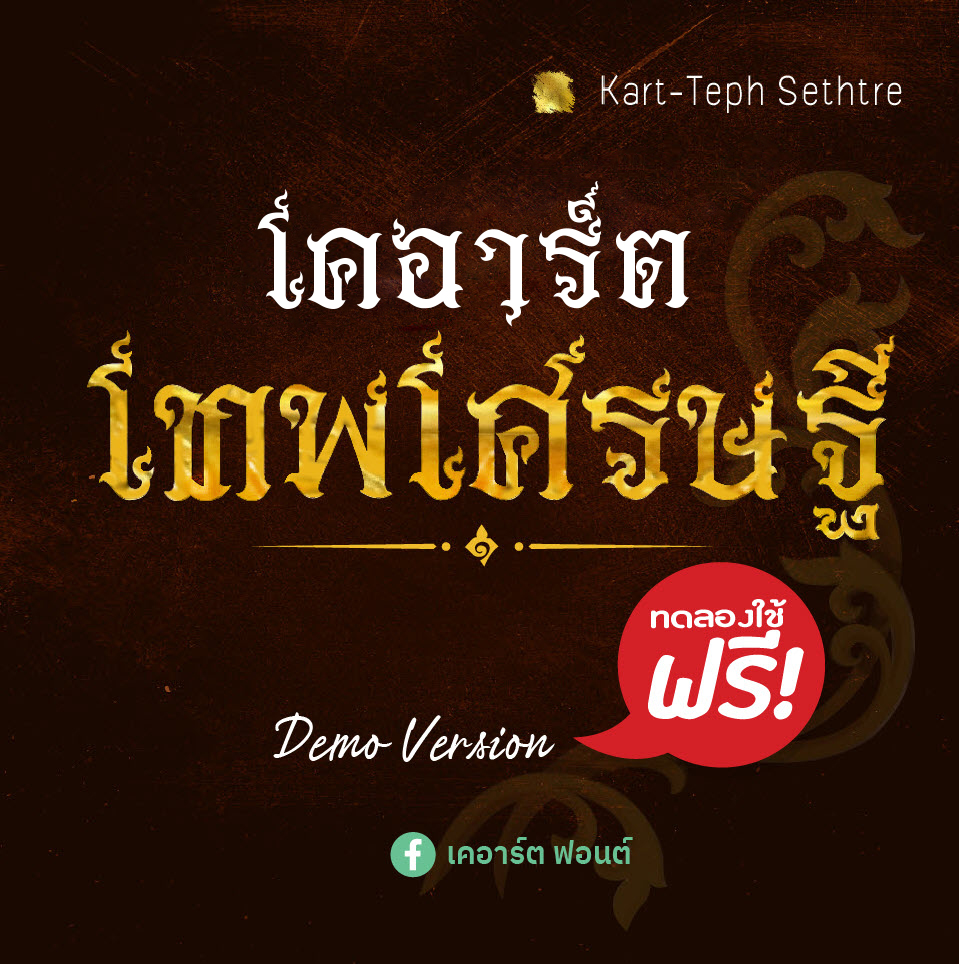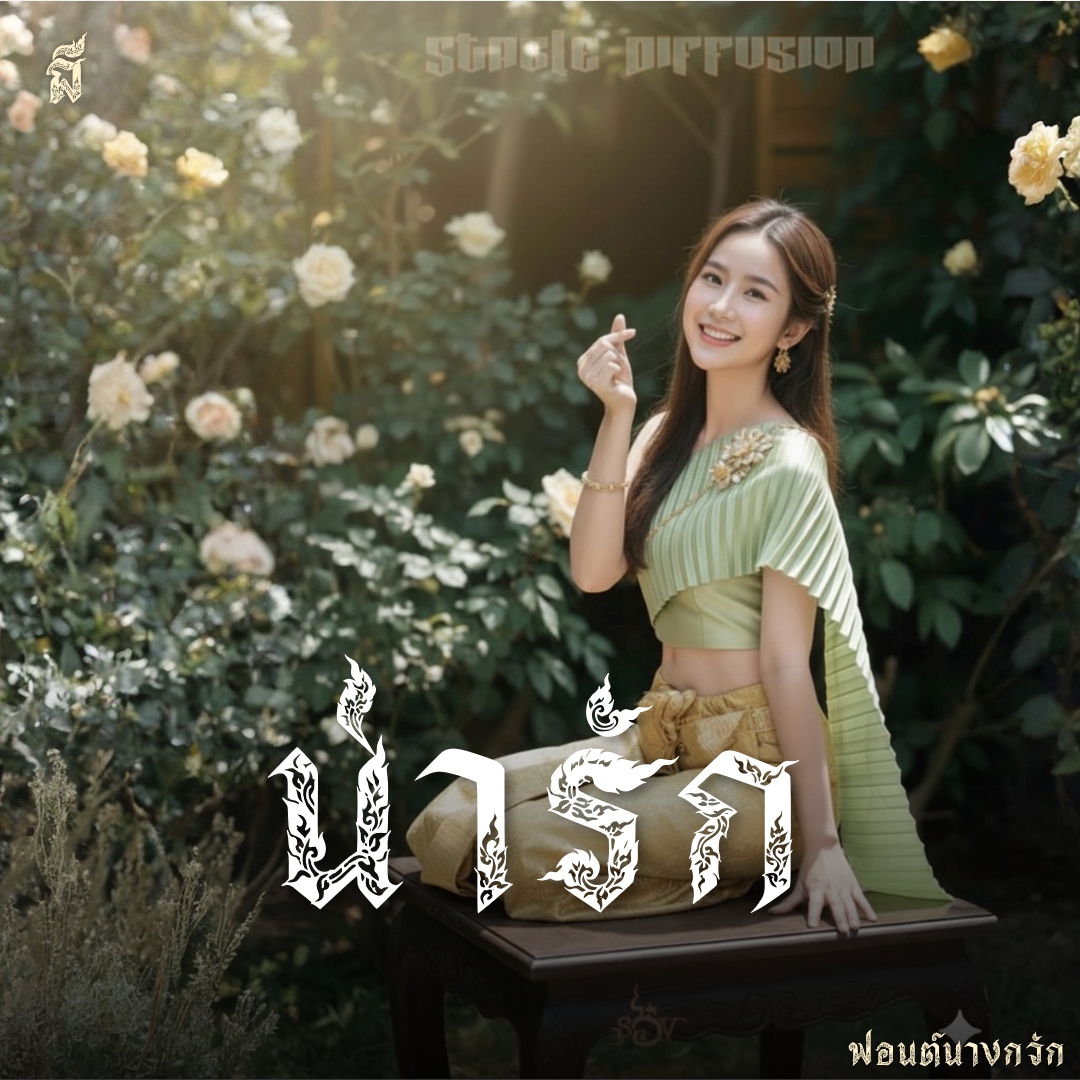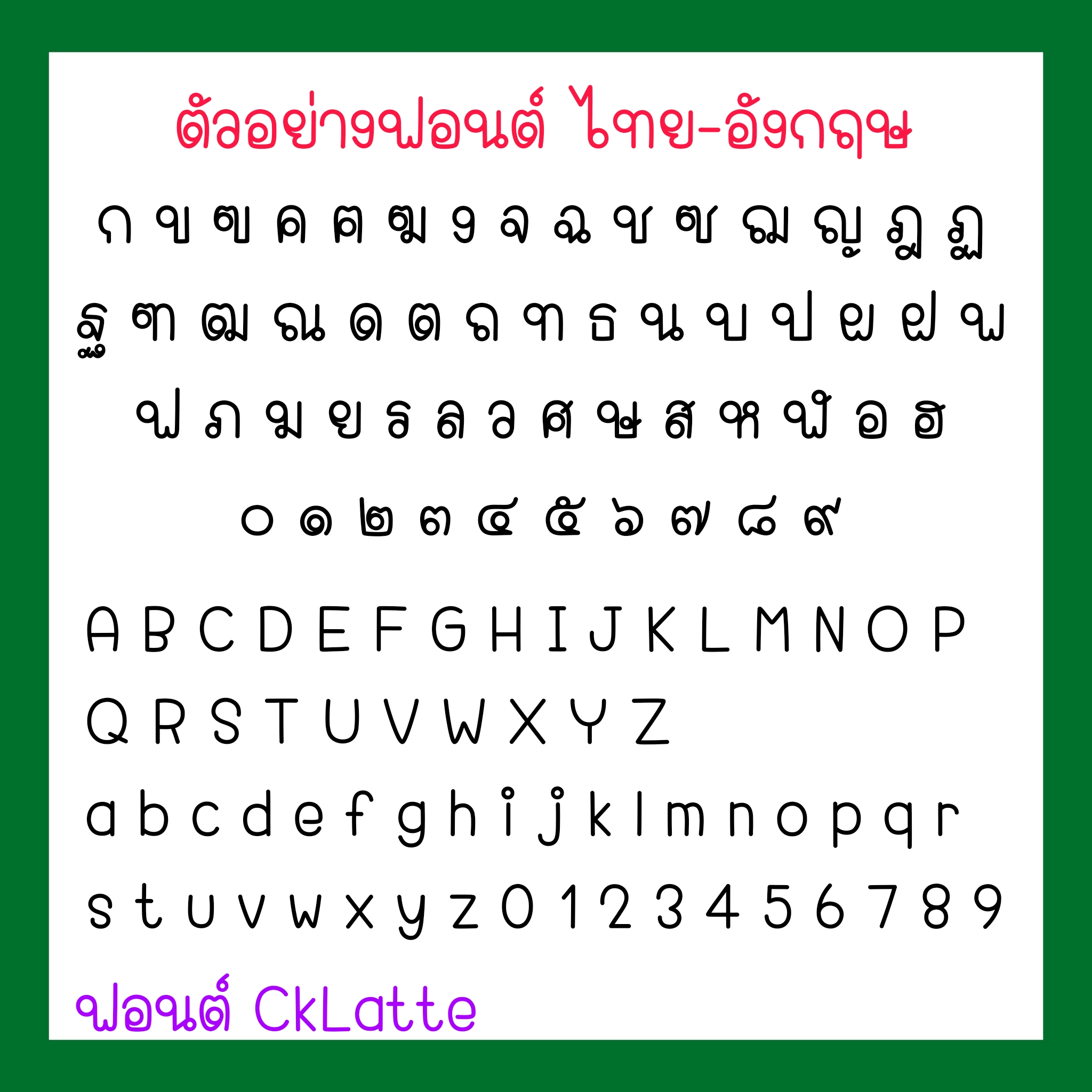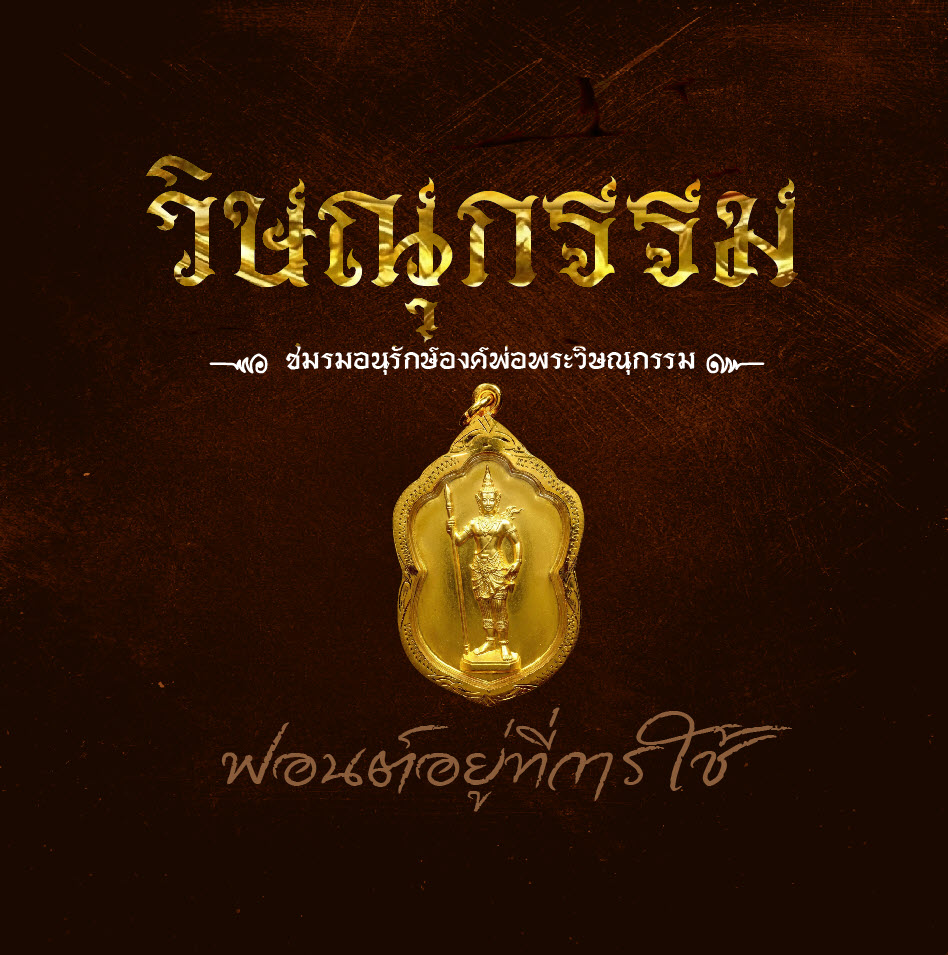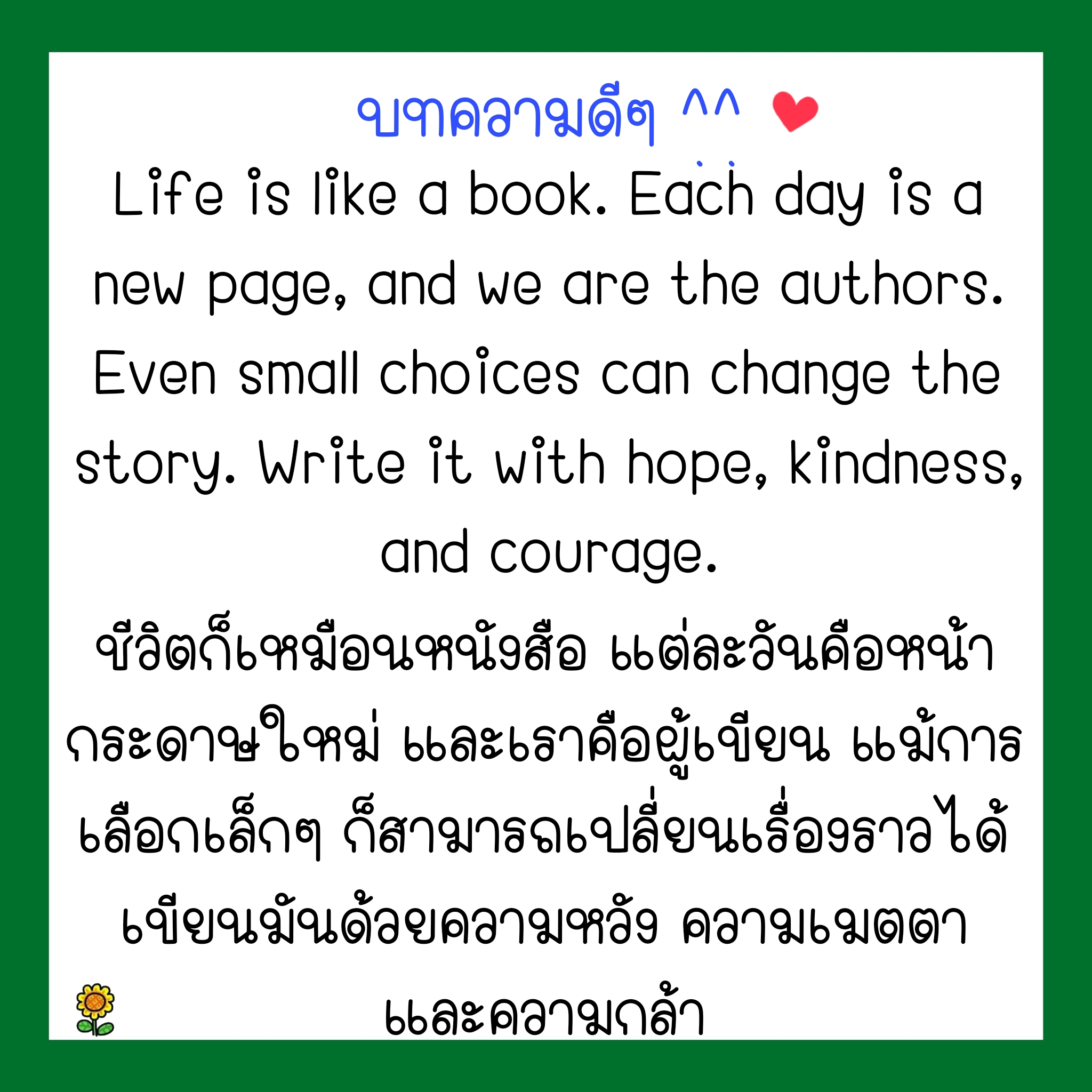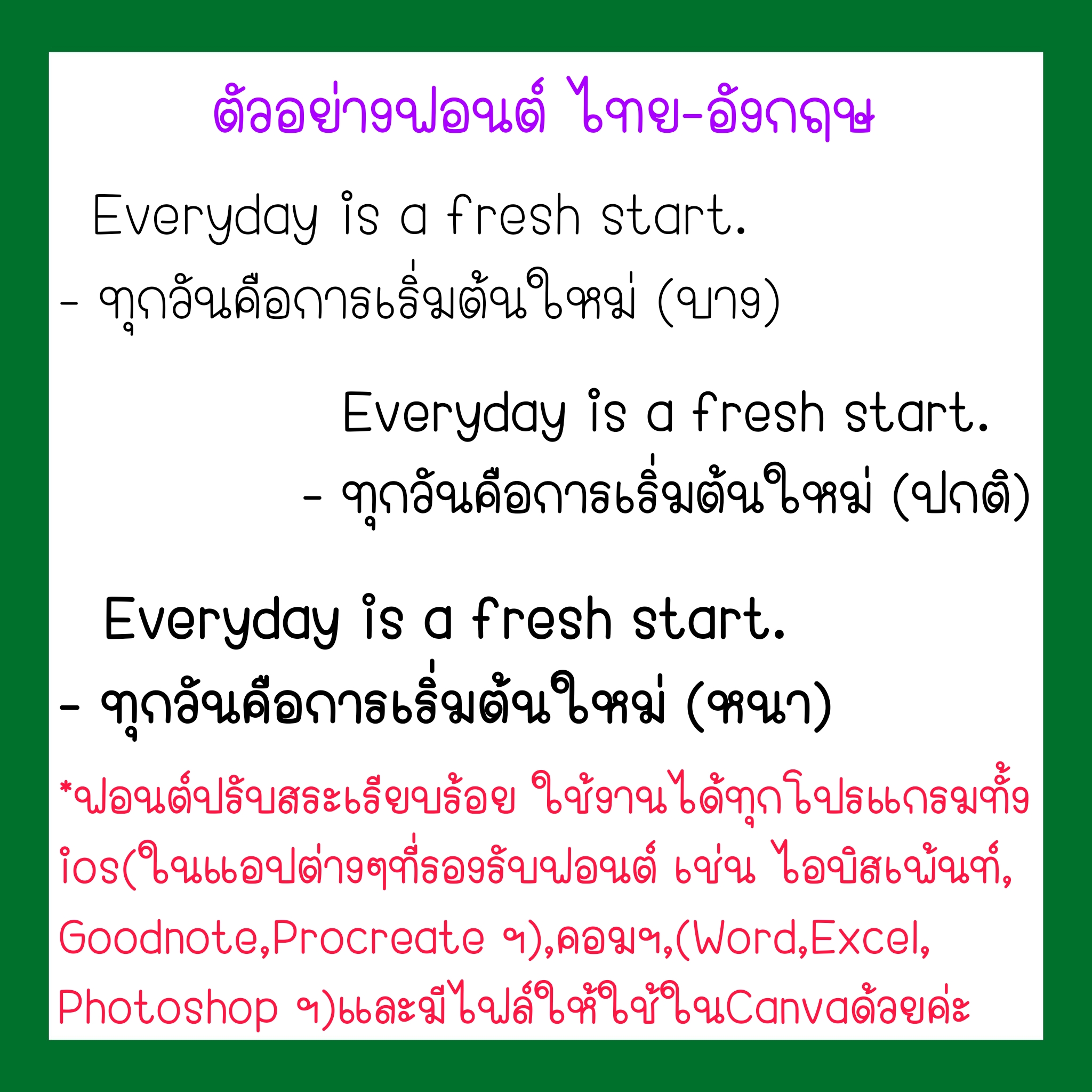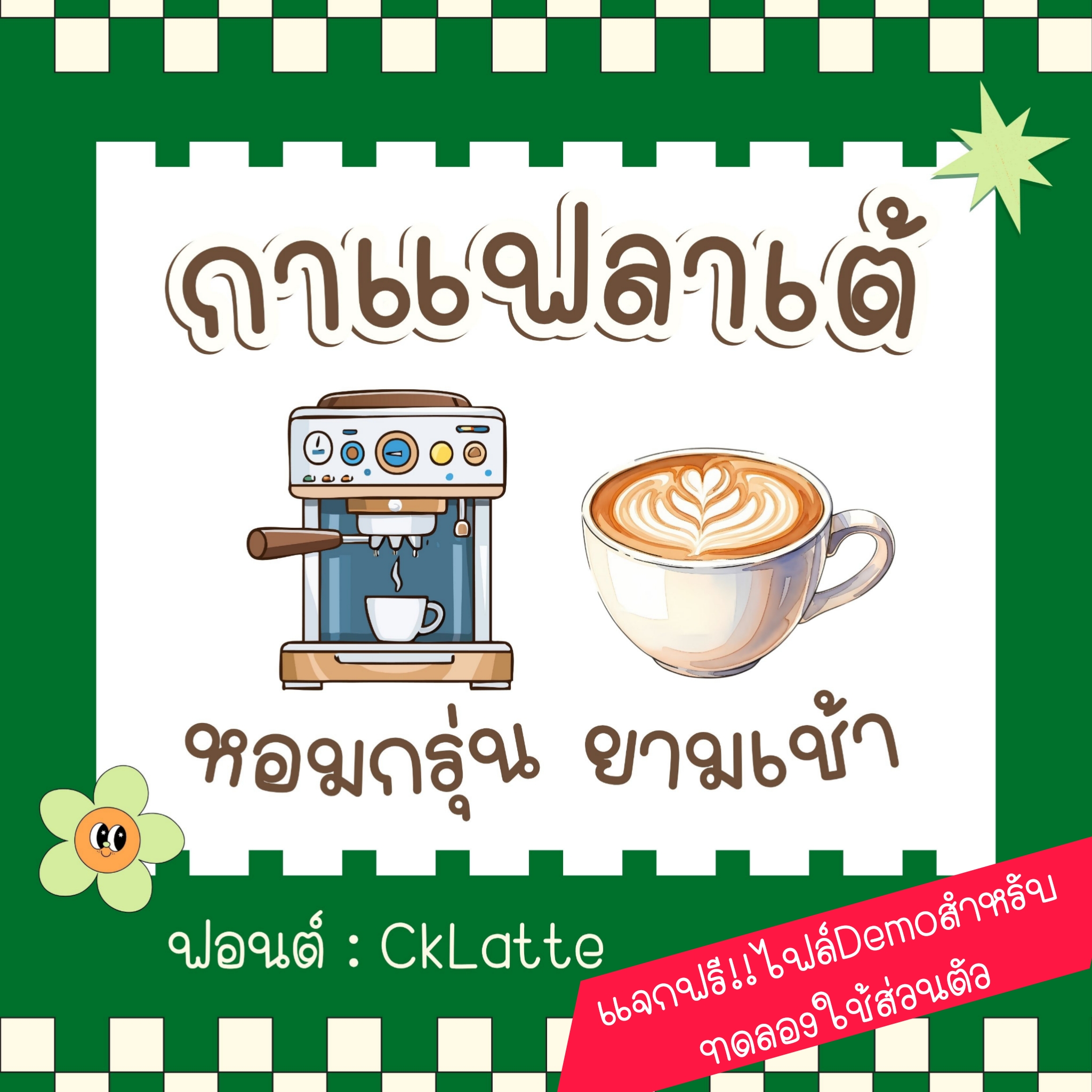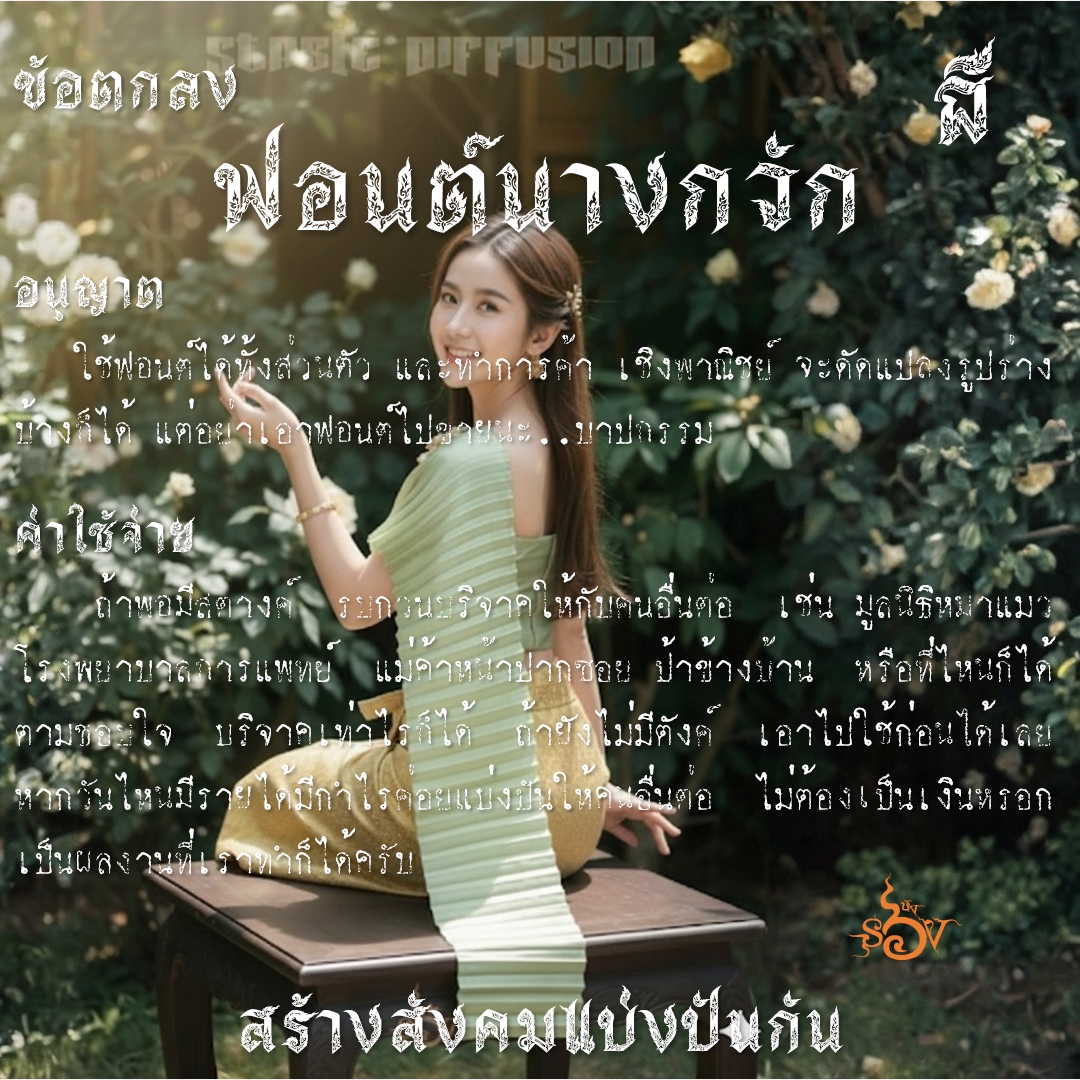
ชื่อฟอนต์ : นางกวัก
นางกวัก ได้ชื่อมาจากคำชี้นำตอนที่ให้ AI gen รูปนางกวัก เป็นจังหวะที่ทดลองให้ AI ผสมลายกับฟอนต์ของเรา ..มั่วๆ จนได้รูปแบบอักษรเหลี่ยม ที่มีลายฉลุ และเส้นลายด้านนอก มารูปนึง ..จึงเอามาต่อยอด ทำเป็นตัวอักษรจนครบ
ฟอนต์ เคอาร์ตเทพเศรษฐี  (Kart-Teph Sethtre) เป็นฟอนต์ที่เขียนในหมวด #ฟอนต์ลายไทย #ฟอนต์พระเครื่อง ครับ
สร้างสรรค์โดย : เคอาร์ตฟอนต์
- ฟอนต์ CkLatte ฟอนต์ลายมือแนวหัวกลมโต ตัวอวบอ้วนอ่านง่าย มีความน่ารักในตัวค่ะ
CalliGraph คาลิกราฟ เวอร์ชั่น 2
SP_DiSi ดีซิ
ฟอนต์ SP_DiSi ดีซิ
ชื่อฟอนต์ : คุกกี้พิกซ์ (GMCpxcookiepix)
ꔛฟอนต์ PANI.หน้าปกเพลง
ชื่อฟอนต์ : เมลลี่พิกซ์ (GMCpxMelliepix)